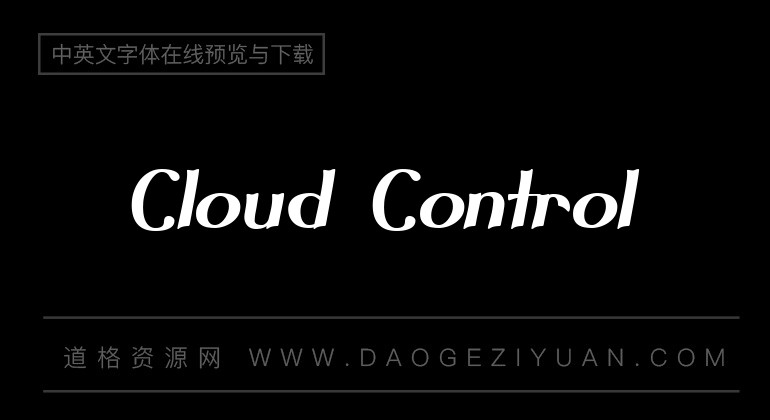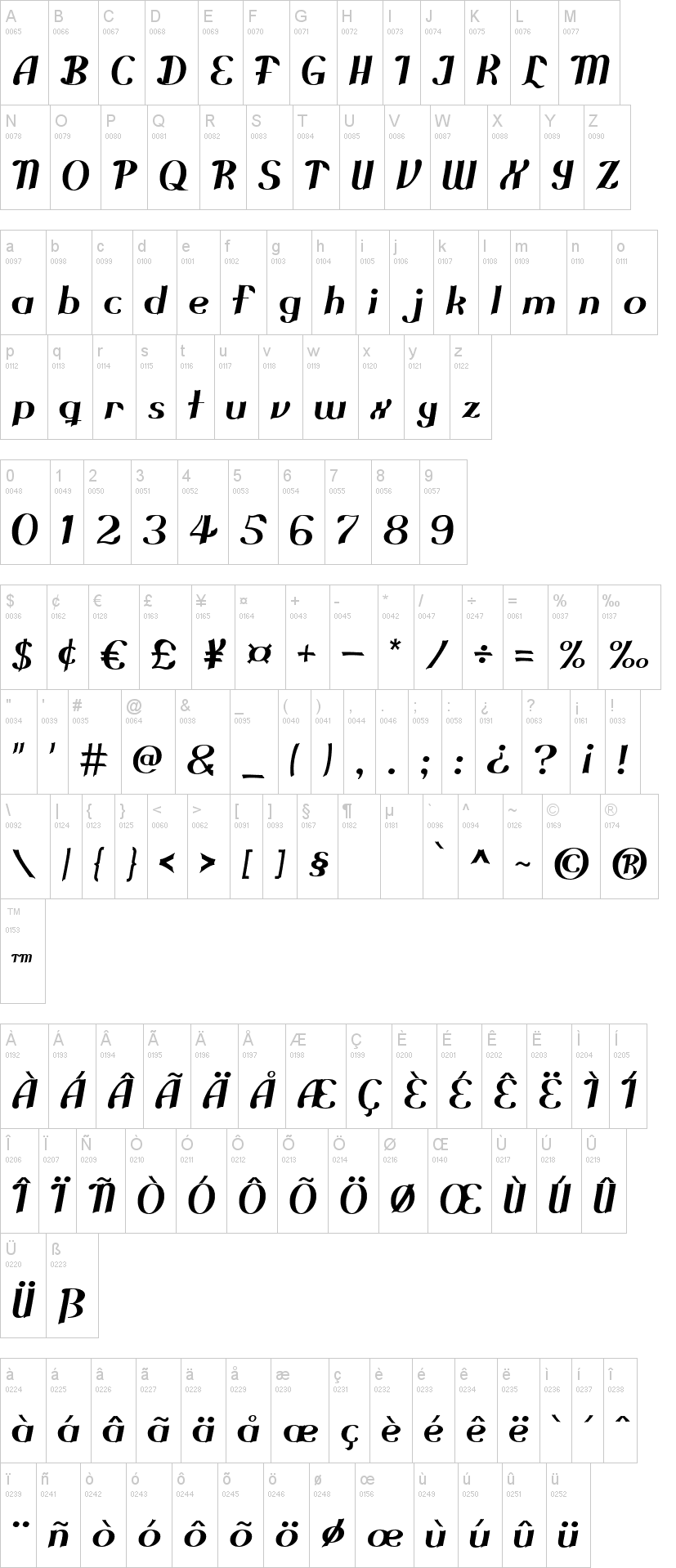
Cloud Control
Cloud Control 字体是一款新的英文字体,由英国设计师 Neil Summerour 创作。它的特点是拥有温柔的曲线,更加现代化的感觉,但又不失传统风格。它的字体非常适合用于标题、标签、按钮等设计中,能够给用户带来清新自然的感受。
Cloud Control是一款非常不错的手写艺术字体,具有很好的视觉感,适合于文化类的宣传设计、商业类品牌的广告和产品包装设计以及个性化文字排版等较多场景。